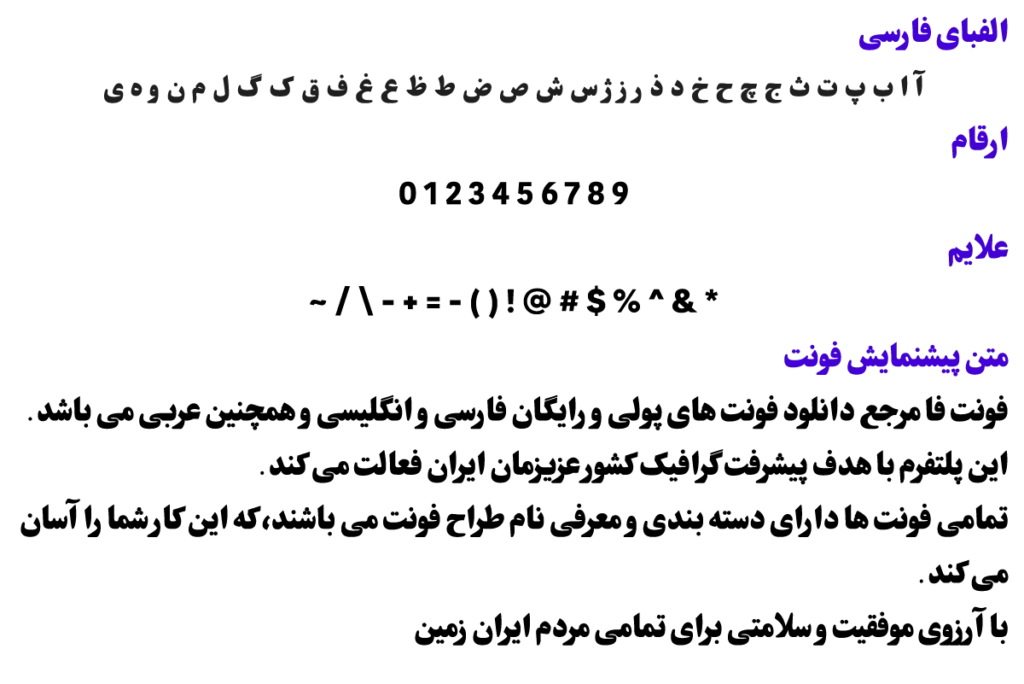
فونت فارسی تیتر پلاس – Titr Plus
سال ساخت فونت: 1400
مجموعه فونت: فونت سری Digi
طراح فونت: مهدی برقگیر نوع فونت: فونت عنوان
توضیحات و معرفی فونت تیتر پلاس
فونت فارسی تیتر پلاس ( Titr Plus ) از مجموعه فونت های آزاد می باشد، و نیز نوع فونت عنوان می باشد.
فونت خوشگل مربوط توسط مهدی برقگیر در سال 1400 طراحی و ساخته شده است.
این فونت بر پایه فونت قدیمی تیتر بازطراحی، چیدمان و توسعه یافته است.
همچنین، این تایپ فیس از نقطه گذاری هوشمند و اعراب گذاری اصولی برخوردار است.
و نیز فونت تیتر پلاس در یک وزن پر رنگ است.